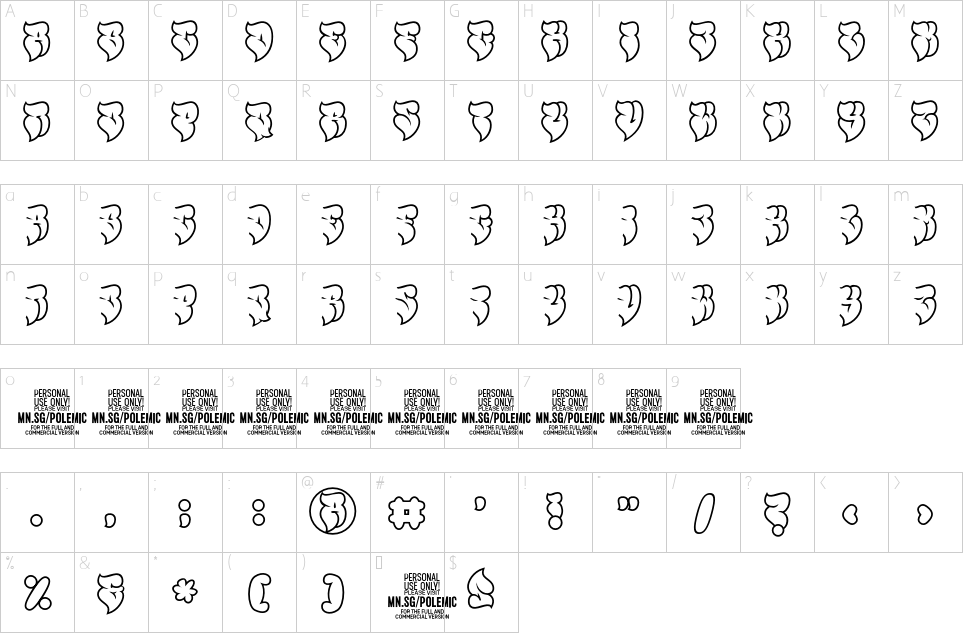
A fonte Polemic é um recurso grátis para designers e ilustradores, ideal para quem busca uma fonte com um estilo robusto e expressivo. Ela foi criada por Måns Grebäck e já foi baixada 177 vezes. Polemic carrega um visual que se adapta bem a um número diversificado de fontes, sendo uma opção agradável para criações de marca, designs de sites ou até mesmo para projetos de design gráfico. A fonte suporta Windows e Mac, tornando-se uma excelente alternativa para quem procura uma fonte de qualidade sem pagar. Download Polemic font e experimente a diferença que essa font pode fazer em seus projetos.